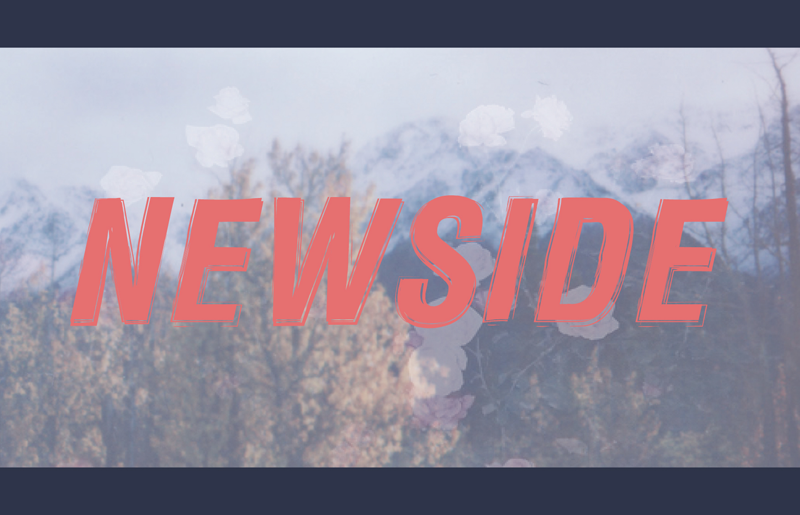
Descubra a Newside FP, uma elegante fonte de sans-serif meticulosamente criada por Hamilton para designers inquietos e apaixonados por criar estilos únicos e modernos. Esta fonte é ideal para projetos que buscam um equilíbrio entre simplicidade e estilo, adequando-se perfeitamente a qualquer tipo de layout ou projeto visual. A Newside FP oferece uma experiência fluida e versátil, adaptável a todos os formatos e tamanhos. Seja você designer gráfico, editor de conteúdo digital ou criador de sites, essa fonte é um recurso essencial para quem busca estilo contemporâneo em sua linguagem visual. Hamilton dedicou-se ao detalhe na criação da Newside FP, garantindo uma experiência de uso fluida e legível. Esta fonte não apenas adicionará uma cara única a seus projetos, mas também ajudará você a se destacar no mercado dos recursos gráficos modernos e versáteis. Para quem deseja usar essa fonte em propósitos comerciais, Hamilton está esperando para fornecer mais informações. Entre em contato com  para adquirir essa fonte excepcionalmente única.